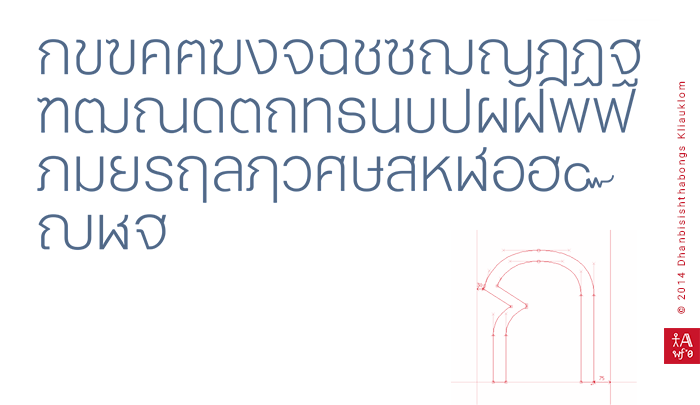
หุ่นยนต์
ฟอนต์หุ่นยนต์ครับ
สวยมาก!!!!!!!!!!!!!!!!!!!!!!!!!!!!!!!
ก.ไก่แบบนี้รักเลยครับ  :07:
กรี๊ดดดดด อยากใช้เลยอ่ะ :25:
สะดุดตา ฟ ฟัน ครับ
เพิ่มเติมครับ
สวยเนี้ยบเพียบพร้อมสุดๆ เลยครับ :05:
รู้สึกว่าสระอามันโล่งๆ อะครับ
ผมจัด side bearing ของ 'สระอา' แบบนี้ครับ แต่ก็อย่างที่ว่ามามันดูโล่งๆ ปัญหาคือพอผมลด side bearing ทางซ้ายลงทางขวามันจะดูแปลกๆ มีท่านไหนมีวิธีอะไรบ้างไหมครับที่ทำให้มันดู OK
จบเลยครับ ฟอนต์นี้   สวยงาม ใช้กันทั่วบ้านทั่วเมืองแน่นอน
ทดแทน กตธด ได้อย่างเหนือชั้นกว่าด้วย :25: :25: :25:
ทดลองลดความกว้างของสระอาดูหรือยังครับ เช่นแทนที่จะเป็น า เต็มๆ โค้ง ก็ให้ลดจงอยมันลงมา หรือใช้รัศมีโค้งที่เล็กกว่าเดิม
อันนี้ผมเทียบกับตัวอย่างฟอนต์เฮลเวไทยก้าครับ ซึ่งดูสัดส่วนช่องไฟลงตัวมาก
ลองลดความกว้างของสระอาลงแล้วดูดีขึ้นครับ  :12:
พี่แอนแนะนำได้มืออาชีพมาก ปรับปรุบเห็นผลปั๊บ :12: